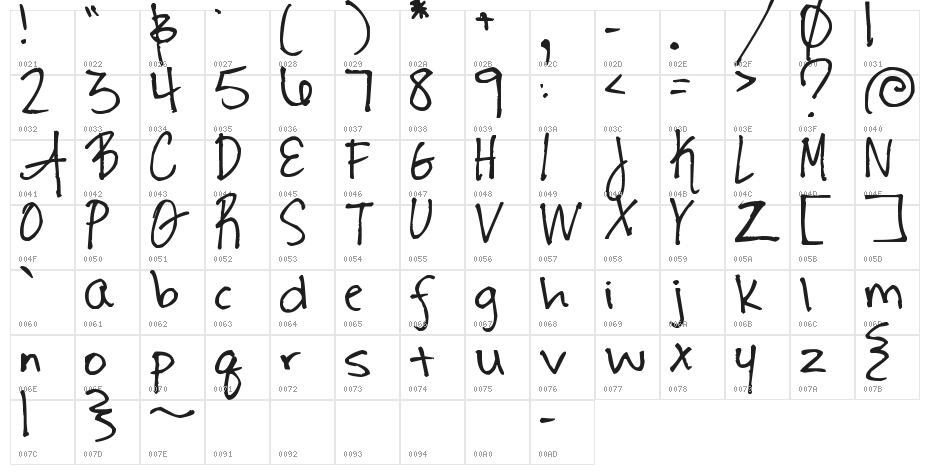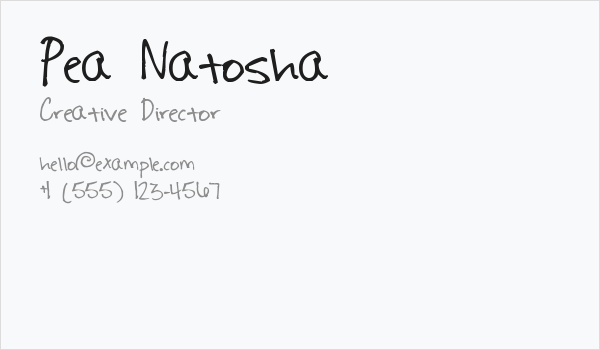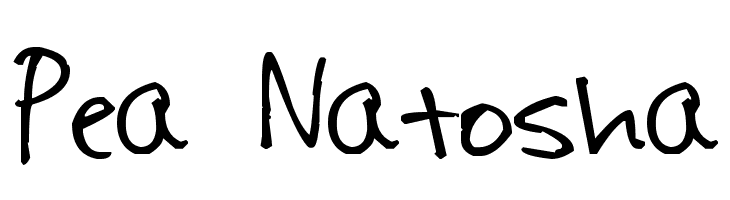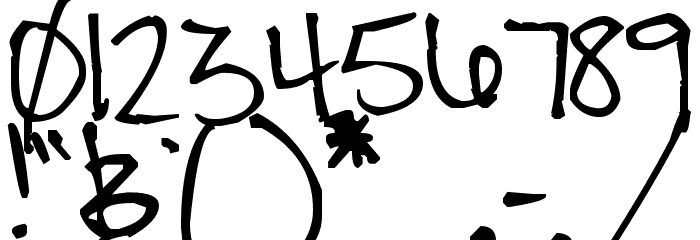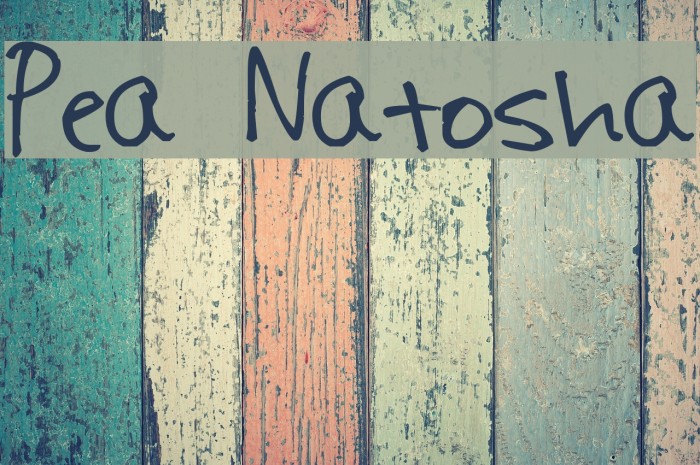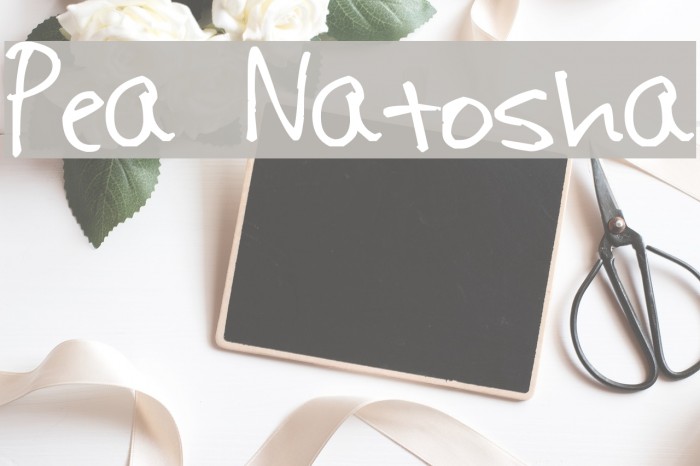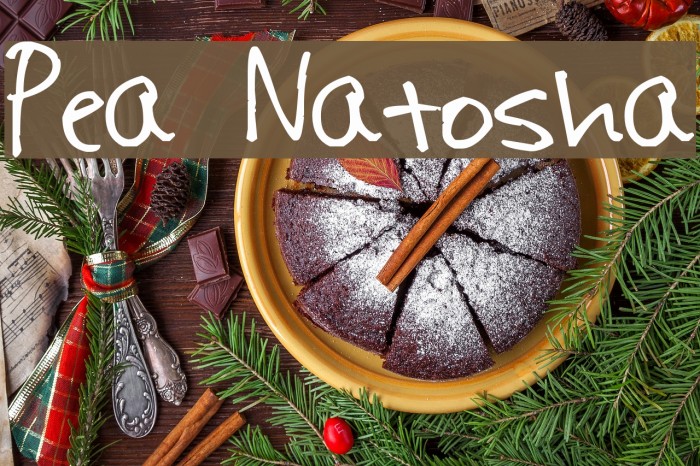
Pea Natosha Font
| Stile generale | Casual, Playful |
| Caso d'uso | Headlines, Informal text, Creative projects |
| Progetti proposti | Ideal for greeting cards, personal blogs, children's books, and creative branding projects. |